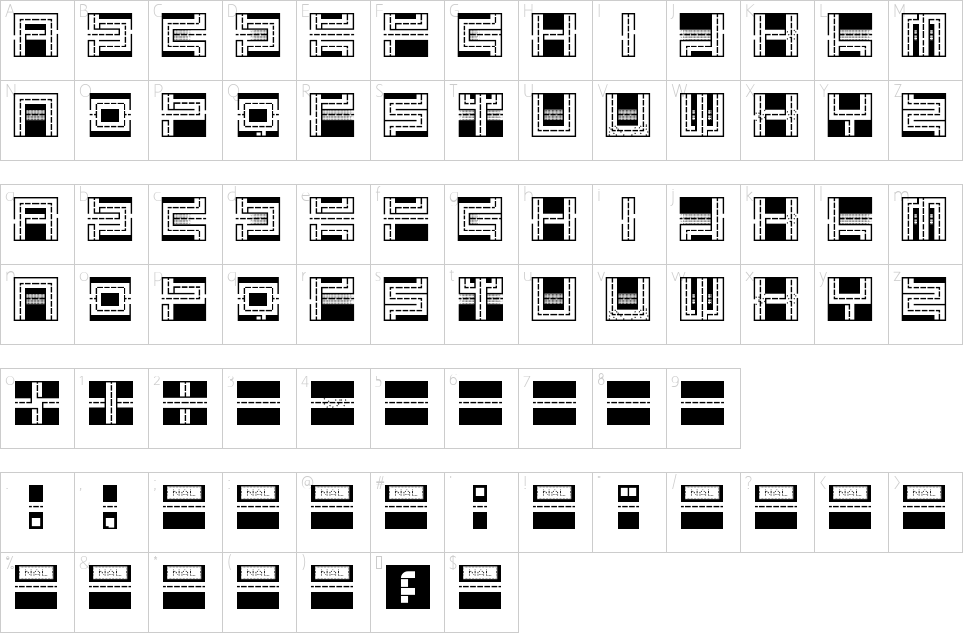
A fonte ‘Melancholic Roadeo’ é uma opção elegante e sofisticada para designers e criadores de conteúdo. Desenhada pelo Designer Chequered Ink, ela oferece um toque melancólico e peculiar que pode enriquecer qualquer projeto visual. Esta fonte é uma delícia para os olhos, especialmente quando aplicada em textos e títulos para dar um toque único e intrigante. Sua simplicidade e originalidade a tornam um recurso indispensável para quem procura algo além da estandardização gráfica. Com seu design único e seu download fácil para Windows e Mac, a fonte ‘Melancholic Roadeo’ é uma ótima escolha para quem busca uma fonte única, versátil e muito versátil. Com apenas 1,708 downloads, é uma fonte ainda mais desejada. Descubra por si mesmo como ‘Melancholic Roadeo’ pode revolucionar suas criações.